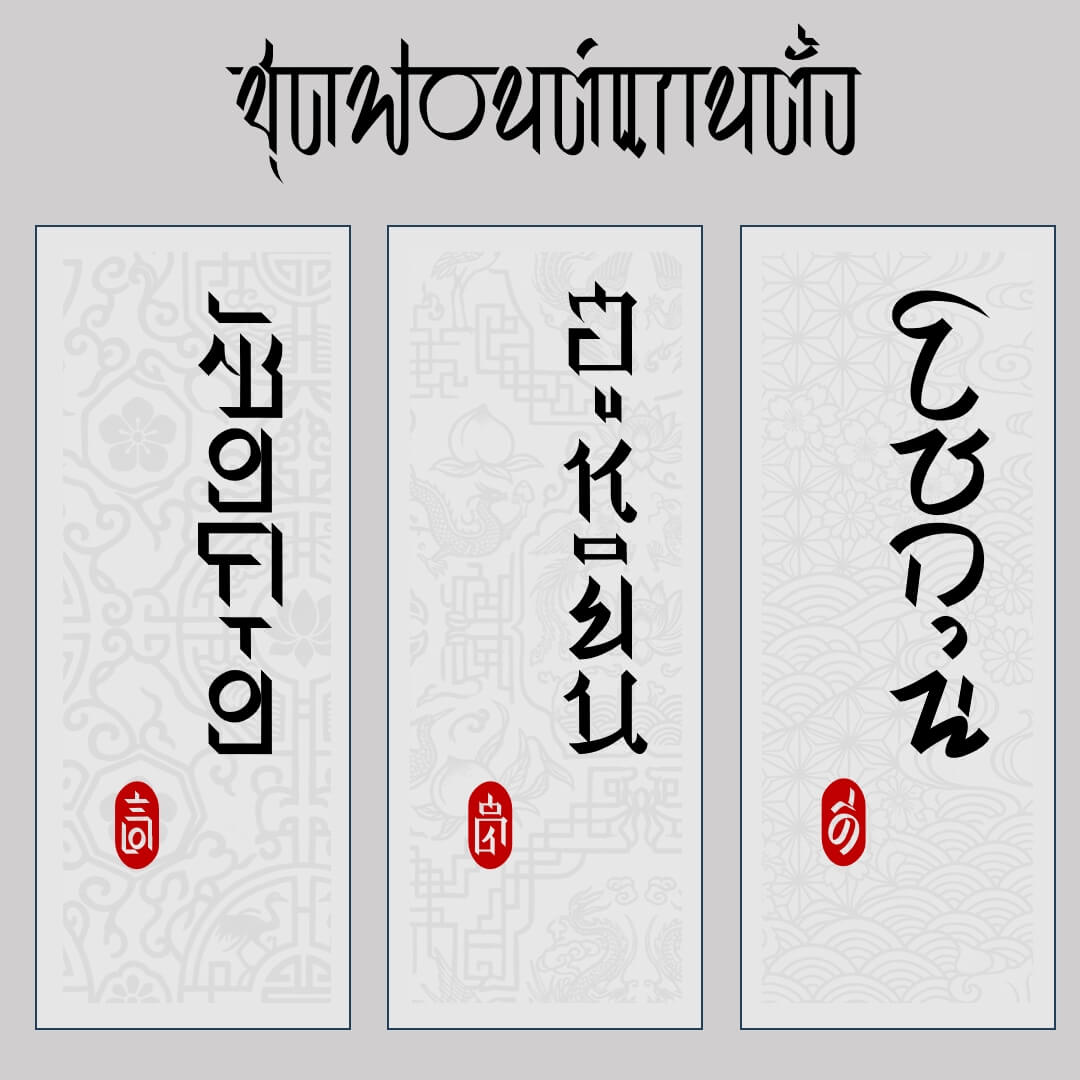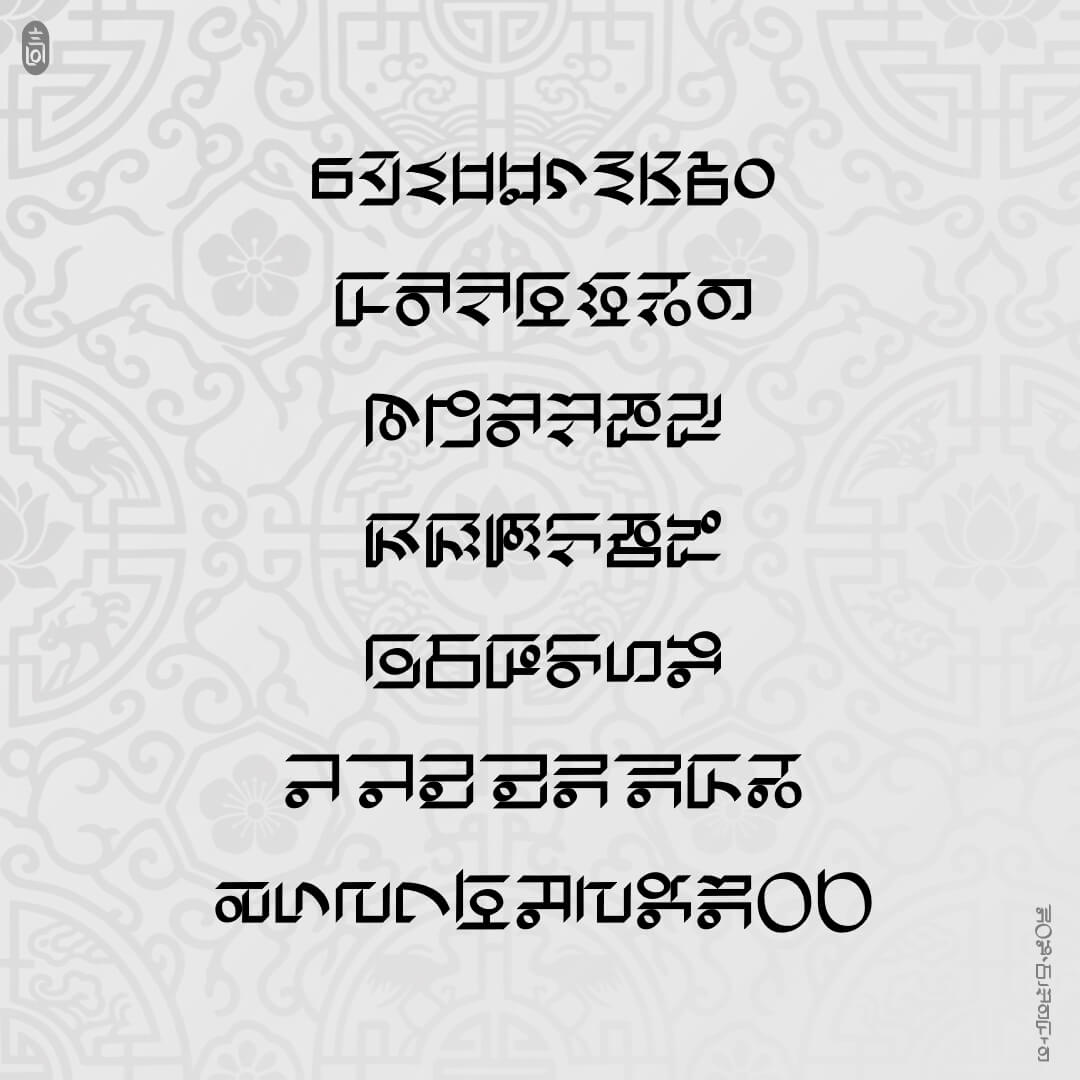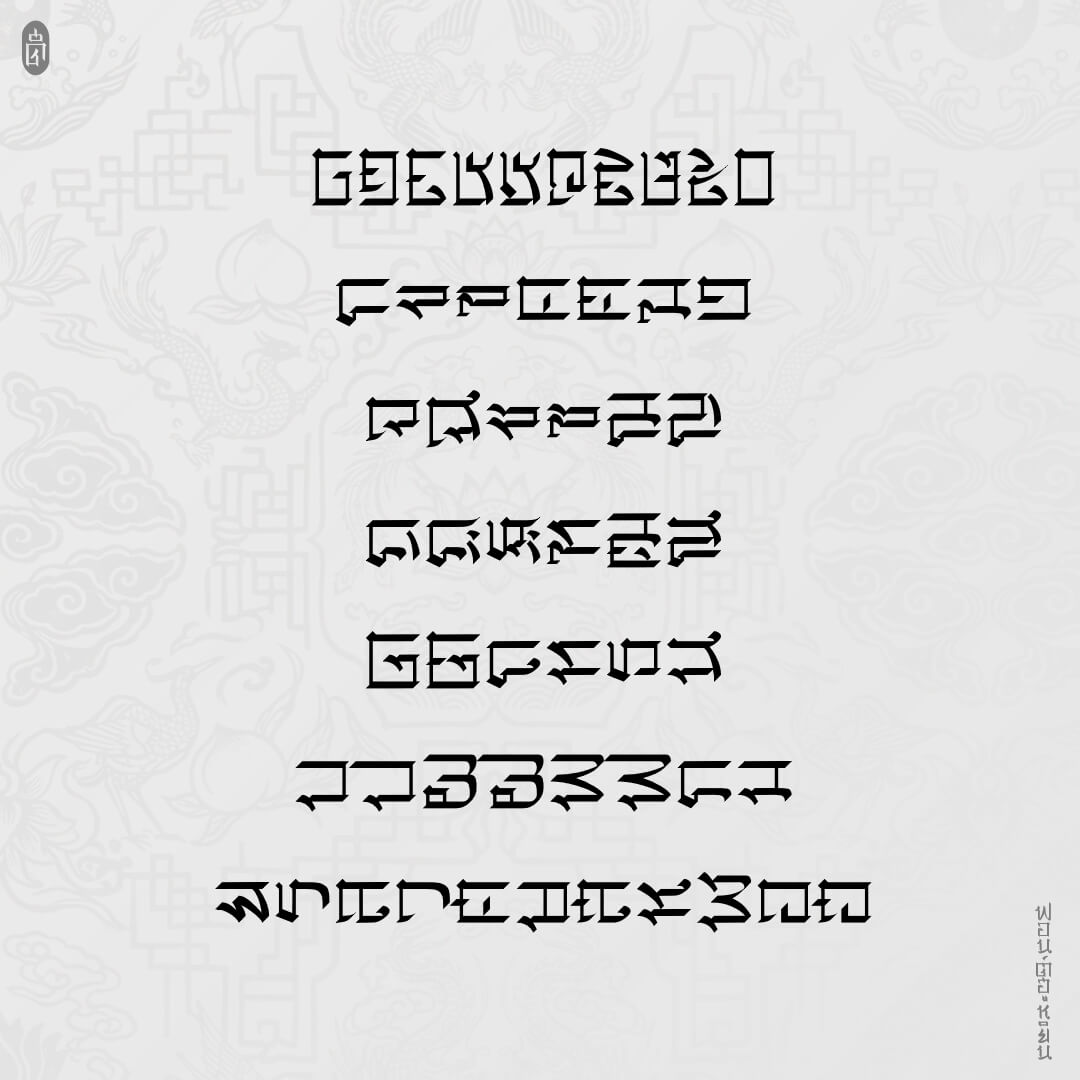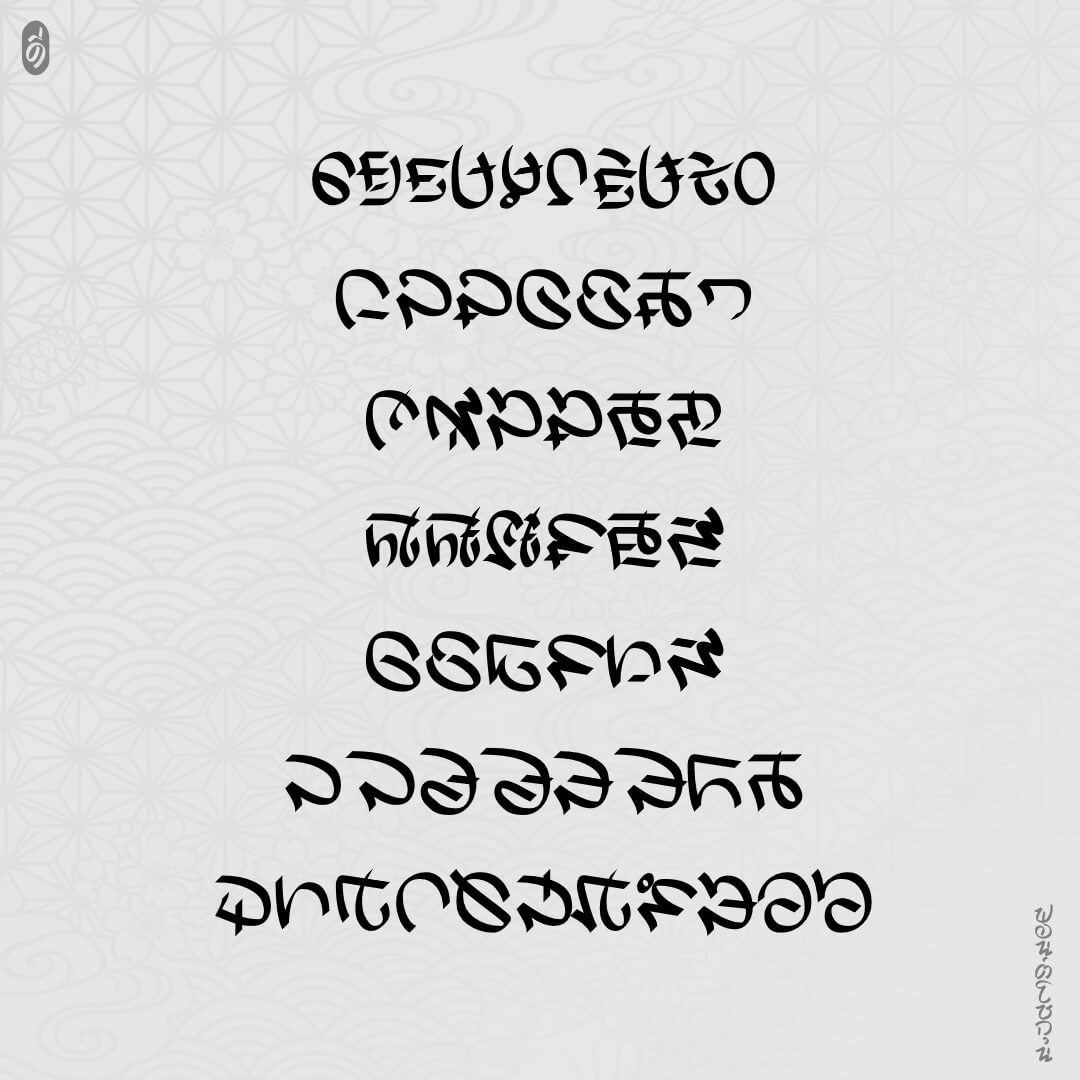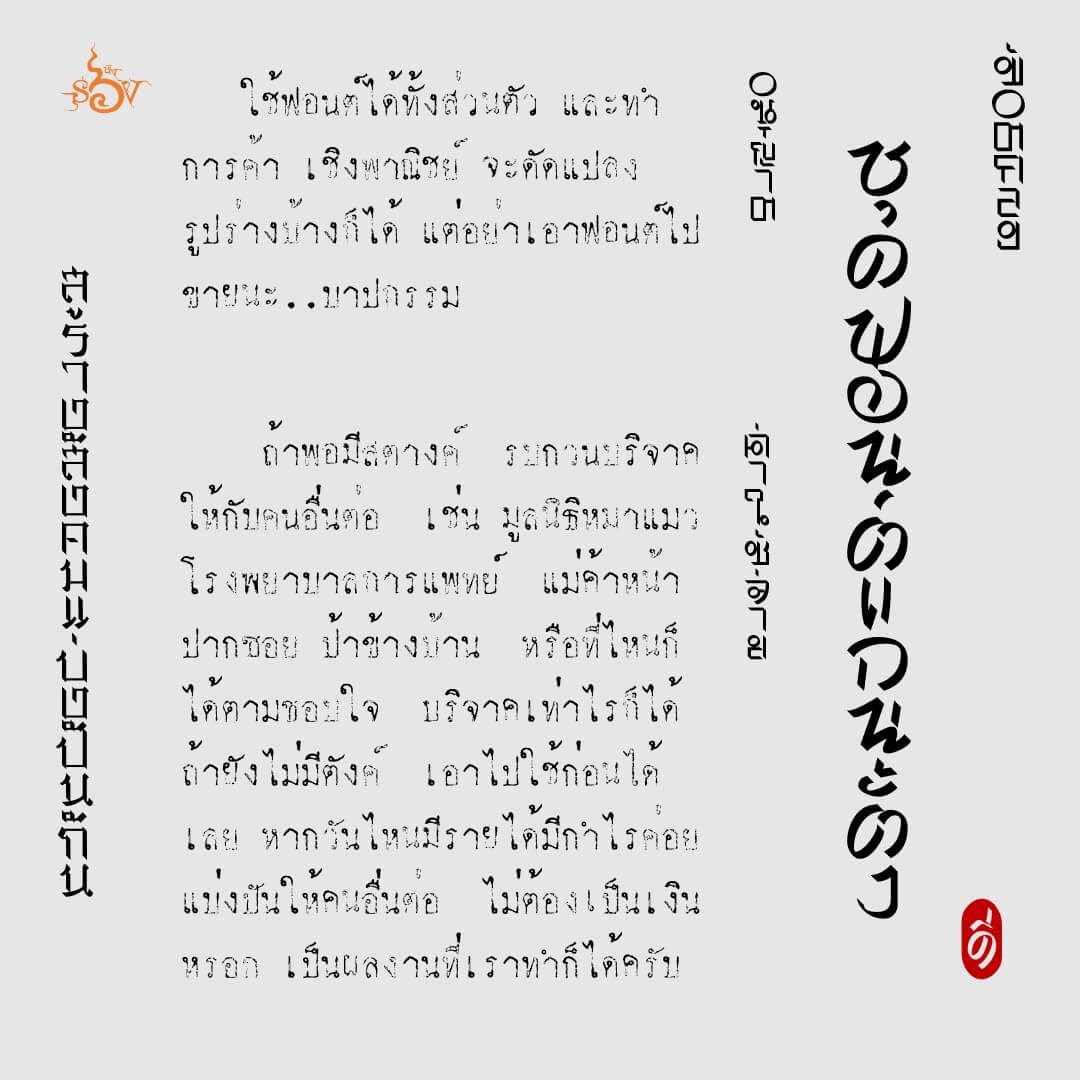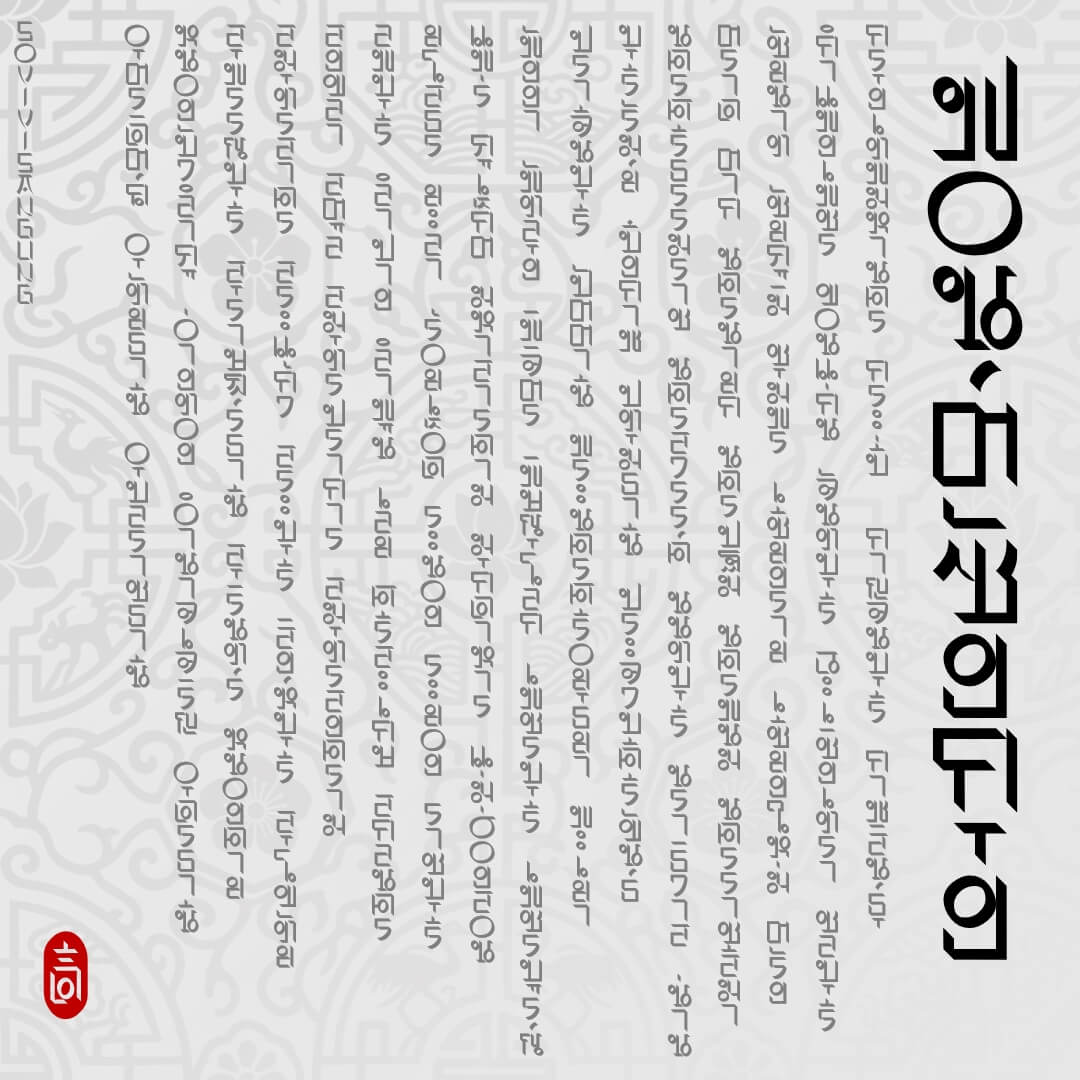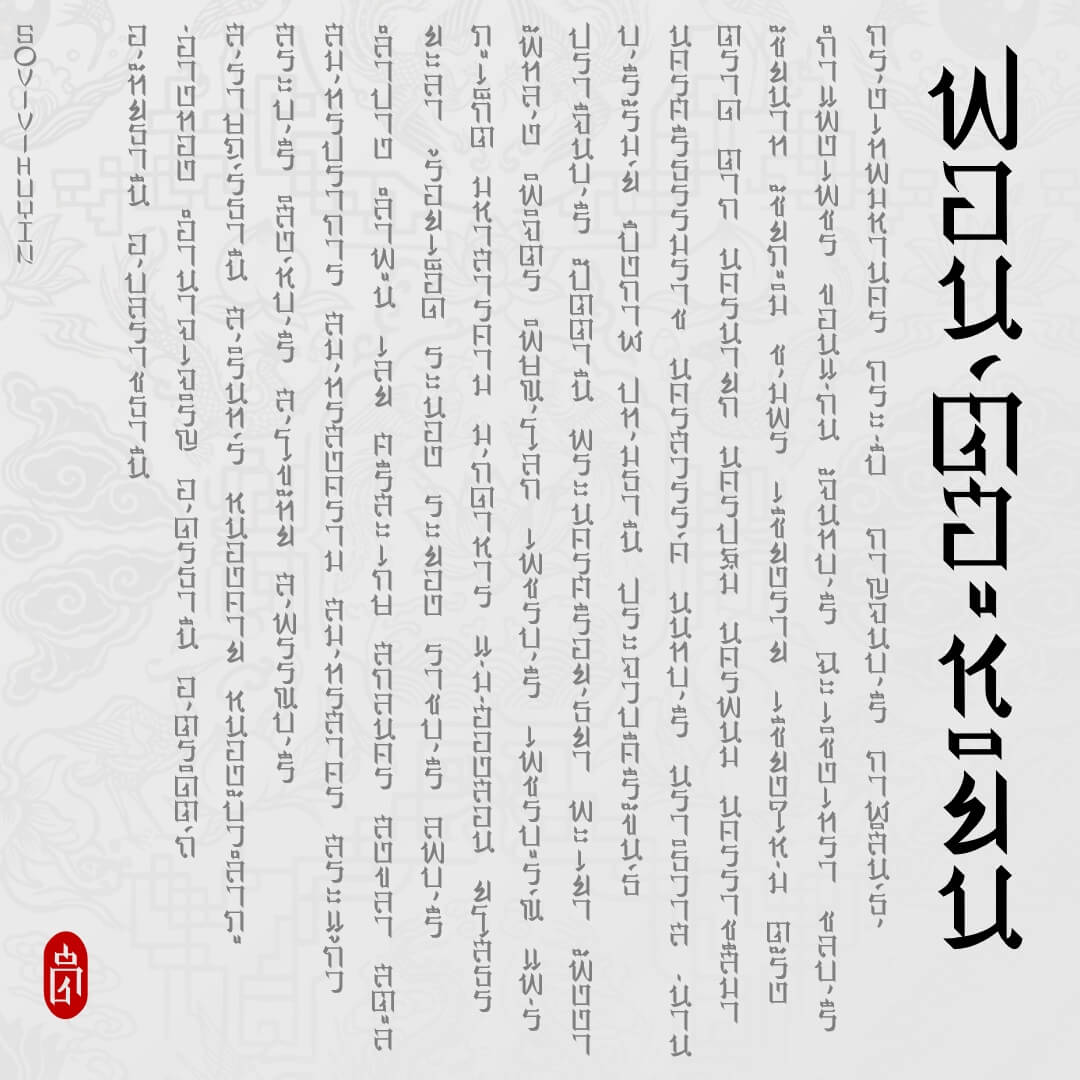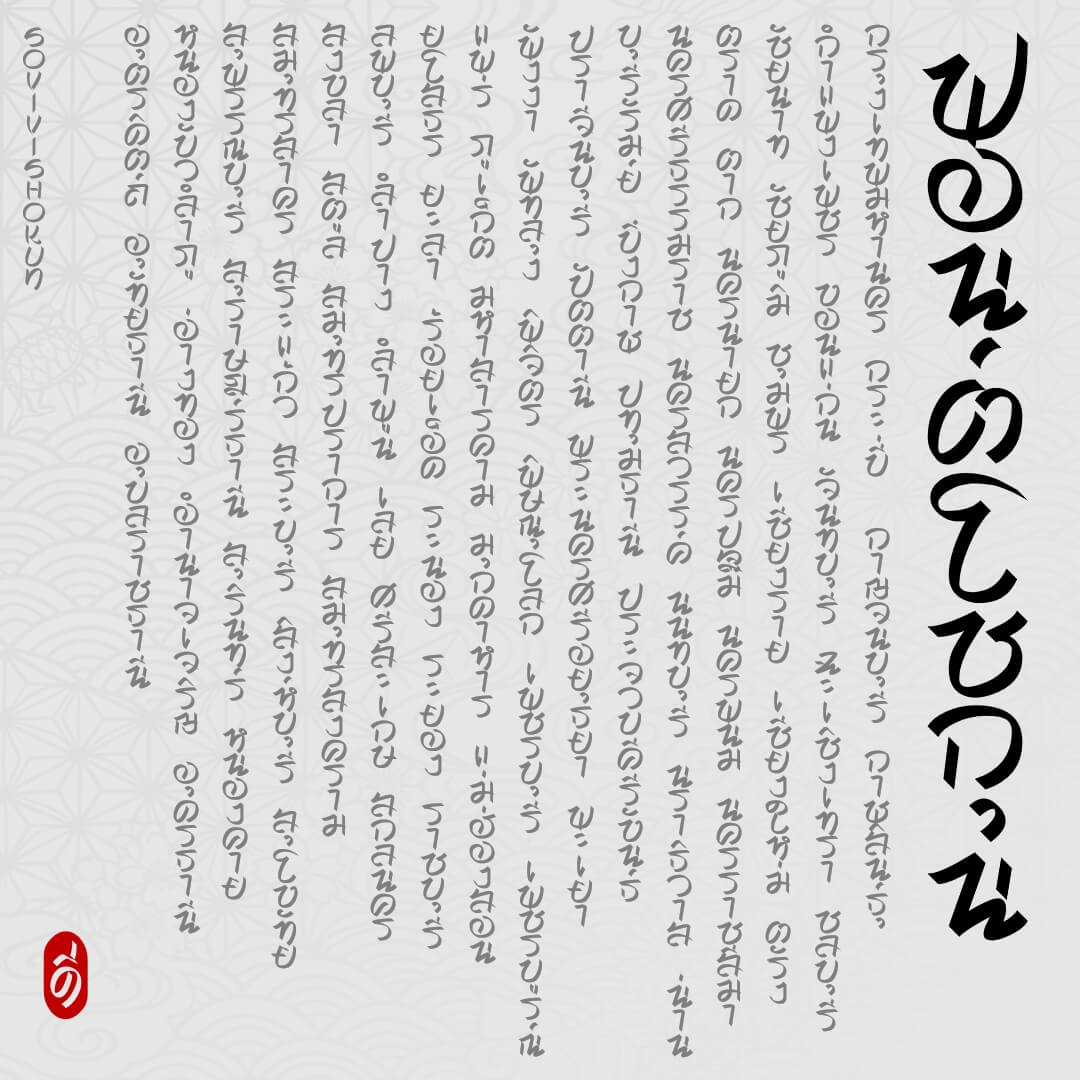
ชุดฟอนต์แกนตั้ง – ออกแบบเพื่อเป็นฟอนต์อักษรไทยเรียงจากบนลงล่าง ซ้ายไปขวา และจัด kerning สระบน ล่าง วรรณยุกต์… ประกอบด้วย 3 ฟอนต์ 3 สไตล์ CJK (SOV_V_Huyin, SOV_V_Sangung, SOV_V_Shokun)
เวลาใช้งานให้เปลี่ยนแกนอักษรแล้วค่อยพิมพ์ หรือพิมพ์ไปก่อนแล้วหมุน 90 องศาตามเข็มนาฬิกา
เบื้องหลังการออกแบบ : ชุดฟอนต์แกนตั้ง
ชุดฟอนต์แกนตั้ง - ฟอนต์ซังกุง (SOV_V_Sangung)
ชุดฟอนต์แกนตั้ง - ฟอนต์ฮูหยิน (SOV_V_Huyin)
ชุดฟอนต์แกนตั้ง - ฟอนต์โชกุน (SOV_V_Shokun)